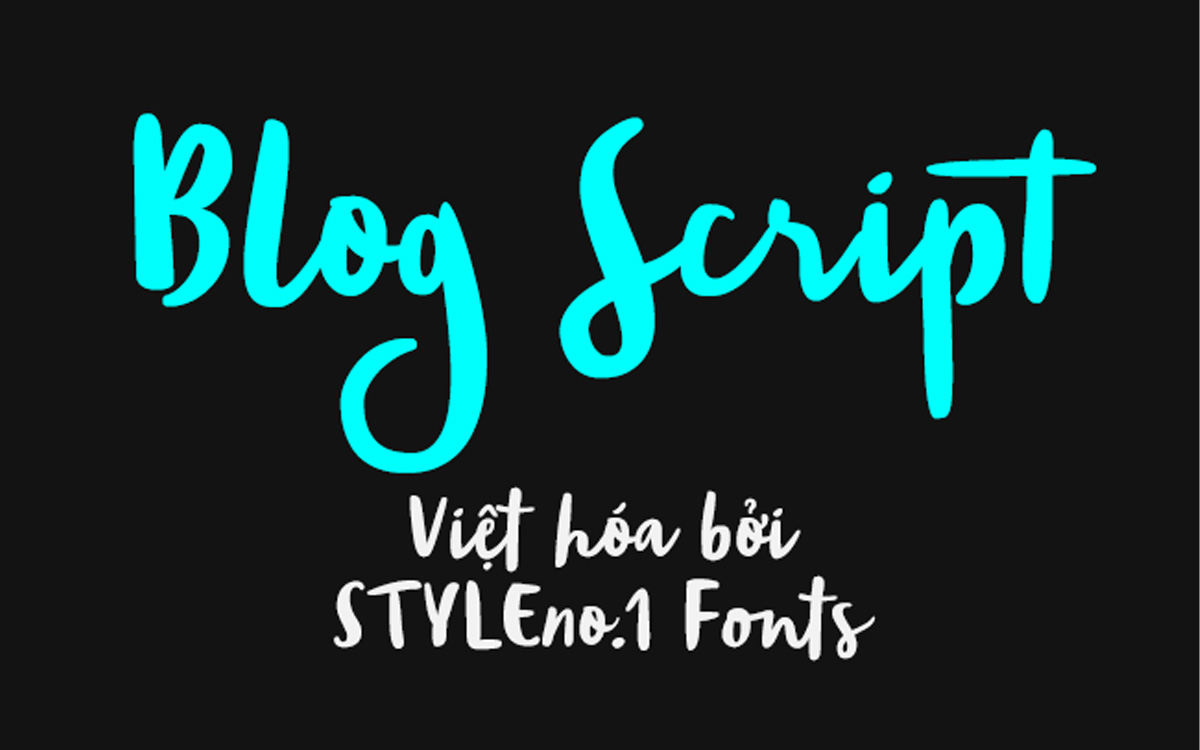
Trong ngày trọng đại của cuộc đời, tấm thiệp cưới không chỉ là lời mời trân trọng gửi đến người thân, bạn bè mà còn là tác phẩm nghệ thuật thể hiện gu thẩm mỹ và câu chuyện tình yêu của cô dâu chú rể. Nếu bạn đang tìm kiếm một bộ font mang phong cách nét chữ mềm mại, tinh tế và đậm chất nghệ thuật thì SVN-Blog Script chính là sự lựa chọn không thể hoàn hảo hơn. Bộ font này sở hữu những đường nét uốn lượn bay bổng như chữ ký tay thật, giúp tấm thiệp cưới của bạn trở nên vô cùng sang trọng và độc đáo.</p>
Font Chữ Viết Tay, Chữ Ký Mềm Mại Cho Thiệp Cưới, Đám Cưới SVN-Blog Script – Giải Pháp Thiết Kế Sang Trọng Và Tinh Tế
Nghệ thuật thiết kế thiệp cưới hiện đại luôn đòi hỏi sự kết hợp hài hòa giữa nét truyền thống ấm áp và phong cách hiện đại tinh tế. Trong đó, các font chữ script dạng chữ ký viết tay luôn giữ vị trí độc tôn nhờ khả năng tạo điểm nhấn thị giác vô cùng ấn tượng. Font chữ SVN-Blog Script được đông đảo các nhà thiết kế đồ họa, các xưởng in thiệp cưới và các cặp đôi yêu thích nhờ vẻ đẹp thanh lịch, mượt mà cùng cảm xúc chân thật mà nó mang lại. Dưới đây là những đặc điểm nổi bật và lý do tại sao SVN-Blog Script lại trở thành lựa chọn hàng đầu cho các dự án thiết kế đám cưới hiện nay.
1. Đường Nét Viết Tay Uyển Chuyển, Mang Đậm Dấu Ấn Chữ Ký Cá Nhân
Điểm đặc trưng nổi bật nhất của font chữ viết tay SVN-Blog Script chính là sự mềm mại, tự nhiên trong từng nét bút. Không bị gò bó bởi những quy chuẩn nét chữ máy tính thô cứng, bộ font này mô phỏng hoàn hảo thao tác đưa bút thủ công của các nghệ nhân calligraphy chuyên nghiệp. Sự đan xen giữa các nét thanh, nét đậm được tính toán tỉ mỉ, tạo nên độ nảy và độ mượt quyến rũ cho từng chữ cái. Khi ứng dụng vào việc in tên cô dâu chú rể trên thiệp cưới, SVN-Blog Script mang đến cảm giác như một lời đề tặng, một chữ ký đầy trân trọng và đong đầy tình cảm chân thành dành cho khách mời.
2. Việt Hóa Hoàn Chỉnh Với Hệ Thống Dấu Tiếng Việt Chuẩn Unicode
Một trong những vấn đề lớn nhất mà nhiều designer gặp phải khi sử dụng font chữ nghệ thuật nước ngoài là hiện tượng lỗi font, hỏng dấu hoặc các ký tự tiếng Việt bị lệch tông so với tổng thể. Font chữ SVN-Blog Script đã được Việt hóa cực kỳ bài bản và tỉ mỉ, hỗ trợ đầy đủ các ký tự có dấu trong tiếng Việt theo chuẩn Unicode. Các dấu thanh như sắc, huyền, hỏi, ngã, nặng cùng các dấu phụ như móc, nón đều được thiết kế khéo léo để vừa giữ đúng quy chuẩn ngữ pháp, vừa không làm mất đi độ bay bổng của dòng chữ. Bạn hoàn toàn có thể yên tâm sáng tạo các nội dung tiếng Việt phức tạp mà không lo lắng về lỗi hiển thị.
3. Ứng Dụng Đa Dạng Trong Toàn Bộ Bộ Nhận Diện Đám Cưới (Wedding Stationery)
Không chỉ dừng lại ở việc trang trí thiệp cưới, SVN-Blog Script còn là công cụ đắc lực giúp bạn đồng bộ hóa toàn bộ không gian nghệ thuật của tiệc cưới. Bộ font chữ ký mềm mại này phù hợp cho rất nhiều hạng mục thiết kế khác nhau:
- In ấn tên Cô dâu & Chú rể: Tạo điểm nhấn trung tâm đầy nghệ thuật trên bìa thiệp và ruột thiệp cưới.
- Bảng chào tiệc cưới (Welcome Board): Tạo sự đón tiếp nồng hậu, sang trọng ngay từ lối vào lễ đường.
- Menu tiệc cưới và thẻ bàn (Table Card): Tăng thêm sự tinh tế, chỉn chu cho không gian ẩm thực của bữa tiệc.
- Bìa album ảnh cưới & Slide trình chiếu: Làm nổi bật các tiêu đề, trích dẫn ngôn tình ý nghĩa của cặp đôi.
- Thiệp cảm ơn (Thank You Card) & Thiệp phản hồi (RSVP): Giữ trọn sự trân trọng đến từng chi tiết nhỏ nhất.
4. Tương Thích Hoàn Hảo Trên Các Phần Mềm Đồ Họa Và Nền Tảng Thiết Kế
5. Khả Năng Kết Hợp Linh Hoạt Với Các Font Chữ Phụ Dạng Serif Và Sans-Serif
Để một tấm thiệp cưới đạt độ hoàn hảo nhất về mặt bố cục thị giác, việc phối hợp font chữ (Font Pairing) đóng vai trò vô cùng quan trọng. SVN-Blog Script đóng vai trò là font chữ tiêu đề (Header Font) tuyệt vời nhờ sự bay bổng nổi bật. Khi kết hợp với các font chữ không chân (Sans-serif) hiện đại hoặc font có chân (Serif) cổ điển cho phần nội dung chi tiết (như ngày giờ, địa điểm tổ chức), tấm thiệp của bạn sẽ đạt được độ cân bằng hoàn hảo giữa tính thẩm mỹ nghệ thuật và khả năng đọc dễ dàng cho người nhận.
6. Nâng Tầm Giá Trị Thương Hiệu Cho Các Nhà Thiết Kế Và Wedding Planner
Đối với các wedding planner, các studio chụp ảnh cưới hay các xưởng in thiệp chuyên nghiệp, sở hữu một bộ sưu tập font chữ viết tay độc đáo như SVN-Blog Script là bí quyết để tạo nên sự khác biệt cạnh tranh. Bộ font mang đến phong cách sang trọng, đẳng cấp chuẩn Châu Âu nhưng vẫn vô cùng gần gũi với văn hóa Việt Nam. Điều này giúp các đơn vị thiết kế dễ dàng chinh phục những khách hàng khó tính nhất, nâng cao giá trị thương hiệu và mang lại những sản phẩm thiệp cưới cao cấp đạt chuẩn nghệ thuật thị giác.
Tổng Kết Và Hướng Dẫn Tải Font Chữ Viết Tay SVN-Blog Script Miễn Phí
Font chữ viết tay, chữ ký mềm mại cho thiệp cưới, đám cưới SVN-Blog Script là một giải pháp thiết kế tuyệt vời không thể thiếu trong thư viện của mỗi designer. Với nét chữ mềm mại, quyến rũ, khả năng hỗ trợ tiếng Việt chuẩn xác cùng sự linh hoạt cao trong ứng dụng thực tế, bộ font này chắc chắn sẽ làm hài lòng bất kỳ ai đang tìm kiếm sự hoàn hảo cho ngày trọng đại. Hãy tải ngay SVN-Blog Script để biến những ý tưởng thiết kế thiệp cưới của bạn thành những tác phẩm nghệ thuật đong đầy tình yêu và cảm xúc.